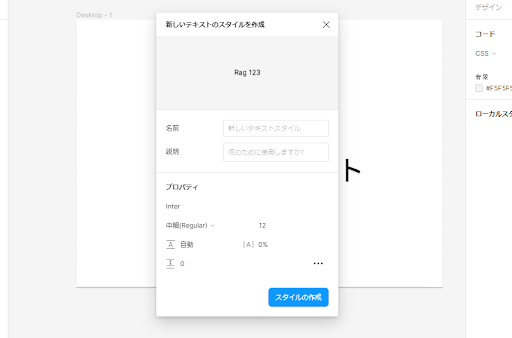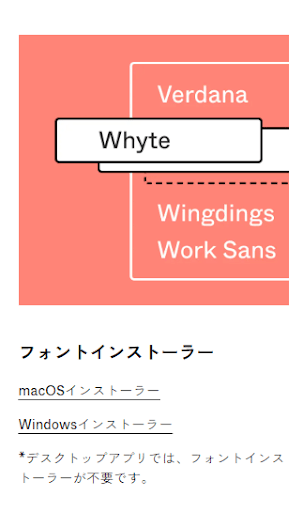
Figmaでフォントを綺麗に見せる。上手な活用法とローカルフォント利用方法
ワイヤーフレームでWebサイトのデザインを考えたり、ホームページを制作する上でフォントやレイアウト決めは大切です。ホームページのレイアウトを整えるためにオンラインで様々なツールが多く利用されており、その中で人気なツールがFigmaです。今回は、Figmaでフォントの上手な活用法とローカルフォントの利用方法を詳しく説明していきます。
Figmaとは?
Figmaとは、オンライン上でワイヤーフレームを作成ができるツールです。Figmaは本来、フォントや画像を編集する機能が備わっていてブラウザ上でワイヤーフレームを作成することができます。ブラウザ上で共同編集をすることができ、チームの人たちとWebデータを共有ができるのが特徴です。
Figmaは、データ管理がシンプルでクラウド上でデータを自動保存することができ、作業途中に落ちてしまった場合でも保存のし忘れを防ぐことができるのが便利です。Figmaの特徴は、自分がデザインをしたいフォントをインストールできます。
Figmaのフォント設定方法
Figmaは、フォントを設定することができる機能が備わっていて様々な種類のフォントを選ぶことができます。ここからは、フォントの設定方法を説明します。
➀編集画面の上のバーに9個のアイコンがあり、右から4番目のTのアイコンをクリックします。
➁ Tをタップするとテキストを入力ができるようになります。
このようにFigmaでは、自分が特定の部分に入力したい位置にテキストを配置することができます。テキストをコピーしたい場合、コピー&ペーストで自分が入力したい箇所にペーストができます。ショートカットキーに対応しており、作業の効率スピードが上がります。
テキストツールが整っており、ペンツールや手のひらツール、テキストに色を付ける機能など様々なツールがあります。テキストをおしゃれしたいときにカラースタイルやローカルフォントで編集ができるのも便利です。
右側の項目には、テキスト項目があり、フォントの種類を選ぶことができ、テキストをインデントで位置を揃えることができます。
Figmaでローカルフォントを設定する方法
Figmaは、ローカルからフォントを使うことができます。ローカルフォントは、公式サイトからインストールができます。
➁ Noto Sans JPが使えるようになり、このフォントを使用することができます。
③ 右の項目のインスペクトからローカルスタイルをクリックします。
④「新しいテキストのスタイルを作成」という画面が出て様々な種類のフォントが選べます。
⑤ 名前の項目に入力して右から一番下のスタイルの作成をクリックします。
⑥ スタイルを完了したら右側のサイドバーのテキストスタイルの欄に階層化された状態で表示されます。Webフォントを使いこなせるようになるとWebサイトのキャッチコピーやテキストの見栄えが良くなり、ユーザーが見る側の印象が変わります。
Figmaで使われている代表的なフォントスタイル
Web制作をする上で読みやすいサイトを作るのにフォント選びは大切です。Webフォントは種類が多く、デザインによって雰囲気がかなり変わります。ワイヤーフレームでデザイン決めの際にフォント選びは大切な要素の一つです。
ここからは、Webフォントをどれを選べばいいのかわからないといった方に代表的なフォントスタイルをご紹介します。
Noto Sansゴシック
Noto Sansゴシックは、Webフォントの中では代表的なフォントデザインです。Noto Sansとは、GoogleとAdobeから共同開発されたフォントでテキストにダイナミックさがなく、ナチュラルなデザインで使うことができます。
Noto Sansの特徴は、サイトの様々な雰囲気に対応しやすく、字の形が優しめなのがポイントです。さらにNoto Sansには、Noto Sans JPや源の角ゴシックなどのフォントの種類が幅広く、太さや見やすさを重視したフォントスタイルがあります。
Noto Sans JP
Noto Sans JPは、Webサイトをデザインする時やレスポンシブ対応にしたい時などに幅広く使われるフォントです。線がきれいでしなやかなデザインなのが特徴で、極細から極太まで太さを選べます。ファイル容量は軽量で、1.5MB程で他のWebフォントより負荷が少なく使うことができます。
視認性はとてもよく、サイトのロゴやキャッチコピーに多く使われることが多く無償で使用できるのがポイントです。
游明朝体
游明朝体は、書籍や小説などに使われている明朝体です。文字の間隔が均等で書籍の見出しなどに使われている場面が多いのが特徴です。游明朝体の字形は、筆書きをモチーフにしたデザインで、文字全体がスッキリとした雰囲気があります。
多くのデザイナーから人気があり、サイトの本文に強弱が付けやすくなったり文字幅が揃えやすくインデントに時間がかからなくなるのがポイントです。
游ゴシック体
游ゴシック体は、文章の文字幅を均等にし、スッキリとした雰囲気を出したフォントです。スペースに余裕があり、サイトの長文を読むときに見やすいデザインで文字の一つ一つ識別しやすいのが特徴です。游ゴシックでは、字型を選択することができ、Light(極細)からBold(極太)まで太さを4種類まで選べます。
Webサイトの文章の見た目を整えたい、キレイなデザインにしたいといった時におすすめです。
ヒラギノ明朝
ヒラギノ明朝は、文字全体がコンパクトでコンパクトさを意識したWebフォントです。書体は、細めで縦の線と均等で全体的に上品な雰囲気が出ているのが特徴です。法律関係や企業のホームページに使用されている場面が多く幅広く活用することができます。
明朝体は、文字の並びがきれいで文章が読みやすく、可読性に優れているのがポイントです。明朝体は、漢字や平仮名のとめ、はね、はらいがしっかり書かれている字形をしていてお年寄りのユーザーにも読みやすい作りになっています。
フォント周りを上手に使いこなす方法
Figmaでテキストのフォントをデザインする際にフォント周りを使いこなせるようになるととても便利になります。Figmaのフォント周りにはオプションがあり、いくつかの意味を知るとテキストの編集の幅が広がることができるようになります。
➀ 特定のテキストをデザインしたい際は、右側の欄のテキストを選択します。フォントの大きさを調整したい時は、Font Sizeの数値を変更するとテキストの大きさを変更することができます。
➁ テキストの間隔を調整したいと思ったら、Letter Spacingという文字間隔を調整することができます。Webサイトの特定のテキストをきれいに揃えたい時はこのLetter Spacingを利用すると見栄えがよくなります。
③ FigmaでWebサイトを制作する際にテキストを読みやすくしたいと思ったらLine-heightを使うことができます。Line heightを活用するとテキストの上と下にスペースができ、要素の周りの見栄えが良くなります。
Figmaには、テキストに色を塗る機能が備わっています。右のテキストの一つ下に「塗り」の欄があり、カラーパレットをクリックすると自分の好きな色を選べます。
ポップアップが表示されてカラーのグラデーション機能が備わっており、好きな色を選べます。カラーコードを入力でき、決まっている色を塗りたい時に入力することができます。
Figmaを利用するメリット
Figmaは、Webサイトを制作するのに便利なオンラインツールであり、オンラインでワイヤーフレームを作成することができます。Webサイト制作でチームで情報共有がしやすいなどの利点が多いここからはFigmaのメリットを説明していきます。
共同作業で自動でデータの保存ができる
Figmaのツールは、サイトを制作する際に複数の人と作業すると相手が編集したときの上書き保存を防ぐことができ、作業の進捗に影響の心配がなくデータを保存することができます。
クラウド上で作業に取り組みやすく、コメントでメッセージを残す機能が搭載されているのでコミュニケーションが進みやすくなるのもポイントです。
データ容量がとても軽量である
Figmaの最大のメリットは、ツールのデータ容量が軽量だという点です。従来のPhotoShopだと、PSDデータのカンバスサイズによって容量が増えていき動作が重くなるといったことが多いでしたが、Figmaだと、拡張子が「.Fig」というデータ単位で使うことができるようになります。
Figmaでは、クラウド上で保存することができるので動作が軽く、利用することができます。
デザイン作成から完成図まで全て対応できる
Figmaは、デザイナー、エンジニアなどの人たちと共同作業をする際にデザインのワイヤーフレーム作成から完成図まで作成することができます。作業スペースで、フォントのデザインや余白、レイアウトなどブラウザ上で直接設定することができます。
今までチームで分業して作業の効率面に悩んでいたらFigmaの機能を活用するとWebサイトの動きやアイデアが浮かびやすくなります。
プラグインが多くカスタマイズができる
Figmaには、プラグインが多く備わっていてプラグインを導入するとWebサイトの制作の効率がさらに上がります。Figmaでは、プラグインを選ぶページに行くと人気順に並んでいて自分が気になるプラグインをインストールすることができます。
もしプラグインがいらなくなったら作業スペースからアンインストールができるので安心して利用することができます。
Figmaのプラグインは、フォントの確認作業を効率化できるプラグインや写真を自動で編集ができるものなど幅広い種類のプラグインを選ぶことができるのでWebサイトの制作で必要なプラグインを使ってみるのもおすすめです。
Figmaを使用する上でデメリット
Figmaはオンライン上でワイヤーフレームの作成ができ、デザインの効率が上がるツールでとても便利な機能がありますが、その逆にデメリットが存在します。ここからはFigmaを使用する上でデメリットをご紹介していきます。
英語表記で人によっては使いづらく感じる場合がある
Figmaは、海外から開発されたオンラインツールで言語が英語で表示されていて人によっては使いづらさを感じる場合があります。Figmaは、日本語のサポート対応していないため、拡張機能に日本語化ができるプラグインをインストールすることができます。
英語が少し苦手で日本語で操作をしたいという方におすすめです
画像などの切り抜きや部分的な合成が対応していない
Figmaは、画像を読み込んでPhotoShopのようにオプションでグラデーションなどの設定ができる反面、切り抜きや合成ができないという点があります。PhotoshopやIllustratorで保存されているマスクが解除されてしまうといったデメリットがあり、人によっては不便に感じるというケースがあります。
テキストの縦書き機能に対応していない
Figmaでは、画像に縦書きのテキストを入れることができないのが難点です。画像やボックスに横書きでしか対応していないのが人によっては不便に感じてしまう場合があります。Figmaは、アプリ開発やWeb制作に向けたツールで、カタログやバナーなどのグラフィックデザインの制作に向いていないのがデメリットです。
まとめ
FigmaはWeb制作をする時にフォント決めやレイアウトなどデザインを決める時にオンラインでワイヤーフレームができるツールです。
Figmaでは、一つの作業環境でフォントの種類を選ぶことができ、Line-heightで行間を変更してテキストのデザインを気軽に整えることができるのがポイントです。
Figmaでフォント選びに迷っている方や新規のフォントのインストール方法を知りたい方はぜひこの記事で参考にしてみてください。